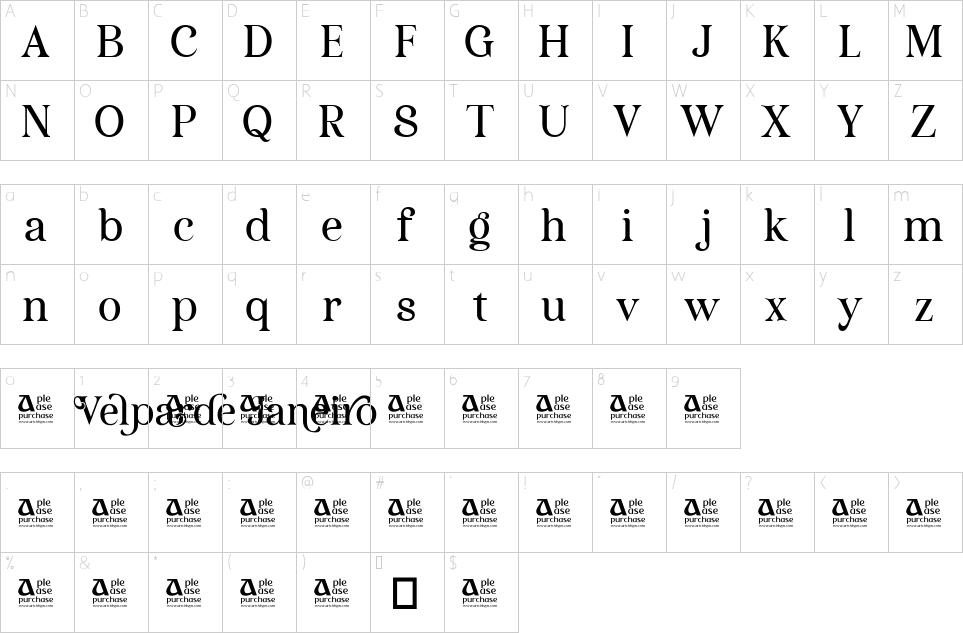
Velparde Janeiro é uma fonte elegante e moderna desenvolvida pela Artchitype Studio, disponível para download tanto no sistema Windows quanto no Mac. Esta fonte é perfeita para quem busca estilização sofisticada nas suas criações digitais ou impressões. A Velparde Janeiro se destaca por sua tipografia suave e fluida, oferecendo uma excelente legibilidade e capacidade de criar diversos efeitos visuais sem perder a elegância. É perfeitamente adequada para textos em sites corporativos, anúncios publicitários ou até mesmo para design gráfico sofisticado. Com um estilo minimalista mas com um toque refinado, Velparde Janeiro é uma ótima escolha para quem busca trazer um toque único e moderno aos seus projetos. Se você está procurando por uma fonte de qualidade gratuita que não comprometa a sua criatividade, esta pode ser a opção perfeita. Adquirir essa fonte pela primeira vez significa mais espaço na sua carteira de recursos gráficos, sem precisar gastar dinheiro extra para obter um design visual superior. Sem dúvida uma adição valiosa ao seu conjunto de ferramentas digitais.